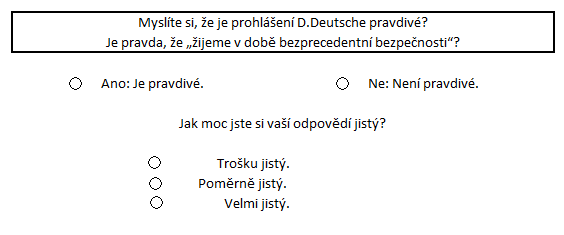
Sherlock Holmes by se divil, aneb co mají fonty společného s marketingem.
Položili jste si někdy otázku, jestli výběr fontů může ovlivnit rozhodnutí čtenáře?
Možná jste se nad tím nikdy nezamýšleli a píšete dál v Calibri. Možná vás ale zajímá, jak váš text podvědomě vnímají čtenáři a co všechno ten výběr tvaru písmenek může ovlivnit. Potom čtěte dál.
Baskervilský experiment provedl novinář E. Morris ve spolupráci s The New York Times v červnu roku 2015 a zúčastnilo se ho přes 45 000 respondentů. Wow, to je hodně lidí, že? Pokud to myslíte s marketingem vážně, i vás by mohly výsledky zajímat! Morris totiž přinesl odpověď na otázku:
„Může font sám o sobě zásadně ovlivnit to, jak vnímáme obsah sdělení?“
Lidský mozek vnímá velmi komplexně. A bylo by naivní myslet si, že když čte nějaké slovo, tak si představí pouze předmět, který ho reprezentuje. Nevnímá jen význam slova, vnímá zároveň tvary písmen, patek, mezery, hrany a křivky. Vnímá i umístění slova v textu. To vše mozek vyhodnotí, jako proces, který probíhá na pozadí našeho vědomí, zpracuje a přiřadí slovu emoci. Emoci, která se sváže s obsahem. Bezpečí, důvěra, kompetence, zábava…
Chiropraktici vědí jasně, které místo na těle zmáčknout, aby aktivovali určitý orgán. Já tvrdím, že stačí změnit tvar patek nebo šířku mezer mezi písmeny, a ovlivníte emoci vznikající v mozku čtenáře.
Zpět k Baskervillskému experimentu.
Skládal se ze tří fází. U prvních dvou se vám bude zdát, že nemají nic společného s marketingem, ale vydržte, ve třetí je překvapivé řešení.
1. FÁZE – vzbudit emoce, zainteresovat publikum.
Morris publikoval článek s přitažlivým titulem „Jste pesimista, nebo optimista?“, který měl za úkol vzbudit v lidech emoce.
Kdo by se nechtěl trošku pohrabat ve svém egu, jestli vidí sklenici poloprázdnou, nebo poloplnou? Lidé milují takové krátké cesty do hlubin vlastní duše. Název tedy přitáhne pozornost a článek má za úkol vzbudit v lidech emoci ohrožení, strachu, prostě základní půd sebezáchovy.Morris v něm popsal trajektorii obřího asteroidu, který v blízké době proletí okolo Země. Přidal vyjádření, ve kterém NASA ujišťuje veřejnost, že žádné reálné nebezpečí nehrozí. Článek uzavírá vyjádřením známého matematika Davida Deutsche:
„Kdyby se kdykoli v historii lidstva až do 21. století přiblížil k Zemi v kolizním kurzu asteroid o průměru 1 km, znamenalo by to smrt podstatné části populace planety. V tomto ohledu, stejně jako v mnoha jiných, žijeme v době bezprecedentní bezpečnosti: 21. století je vůbec první období, kdy víme, jak takovému nárazu, který může nastat přibližně jednou za 250 000 let, zabránit.“
2. FÁZE – zapojení čtenářů.
Na konci článku je online hlasování, ve kterém čtenáři, kteří jsou již zainteresováni díky vzbuzeným emocím, vyjádří svůj postoj k vyjádření matematika Deutsche. Věřím mu, nebo ne?
Někteří mají strach, berou článek vážně. Jiní jsou v klidu a spoléhají na „dobu bezprecedentní bezpečnosti“. A další hlasují jenom ze zvědavosti. Jde přece jenom o to, kolik z nás je optimistů a kolik pesimistů…
3. FÁZE – odhalení pravdy
Překvapení přichází.
E. Morris neměl v úmyslu testovat optimismus, či pesimismus, ale vliv jednotlivých fontů na posouzení důvěryhodnosti tvrzení.
Tvrzení = prohlášení matematika Deutsche a šlo o to, jestli lidé vnímají, jakým fontem je napsané a zohlední to ve svém rozhodování „tvrzení je pravdivé“, nebo „tvrzení není pravdivé“. Právníkovi, který přijde na jednání v šusťákách, také asi uvěříte hůře, než pokud se dostaví v obleku…
Ale jak to provedli?
Ve spolupráci s redakcí The New York Times byli respondenti náhodně rozděleni do šesti skupin. Každé z nich se zobrazil jiný online test (obrázek z fáze 2). Přesněji, text byl stejný, ale napsaný JINÝM FONTEM. Morris vybral tři patkové a tři bezpatkové fonty. Baskerville, Computer Modern, Georgiu, Helveticu, Comic Sans a Trebuchet. Podívejte se, jak vypadají:
4. FÁZE – výsledek
Výsledky byly neuvěřitelné.
Experiment jasně prokázal, že lidé reagují na „důvěryhodnost“ fontu a jeho výběr má velký vliv na to, jakému tvrzení věří více a jakému méně.
Jednoznačným vítězem se stal font Baskerville.
Morris poté zveřejnil v novinách závěr testu s vysvětlením:
„Všichni víme, že jsme ovlivňováni řadou faktorů – o mnohých z nich ani nevíme. Mohou být fonty jedním z nich? Může pouhý výběr fontu ovlivnit, zda budeme věřit jedné věci spíše než jiné? Mohou fonty fungovat jako neviditelné kouzlo? Nebo kletba?
Nechápejte mě špatně. Zásadní pravda ve větě „Zlato má atomové číslo 79“ není závislá na fontu, kterým je napsána. Tato věta platí bez ohledu na to, zda je zobrazena v Helvetice, Georgii nebo dokonce nešťastném Comic Sans. Ale bude pro nás jednodušší uvěřit, že zlato má atomové číslo 79, když si to přečteme v Georgii, kterou používá The New York Times online, spíše než v Helvetice?“
Baskerville nezvítězil náhodou, je to patkový font, starý 250 let. Působí jako anglický gentleman (na rozdíl od Comic sans, který je takový neseriózní adolescent). Má pevné základy, harmonické proporce a budí důvěru. Podobný font používají seriózní noviny nebo právníci pro své smlouvy. Prostě někdo, na jehož slovo se můžete spolehnout. A je vidět, že i lidé, kteří se nad fonty nikdy nezamýšleli, tento „vzkaz“ podvědomě vnímají a fontu Baskerville důvěřují.
Můj oblíbenec je už od vysoké Garamond. Seminárky jsem psala velikostí 13, aby byl čitelností srovnatelný s tehdy dominantním Times New Roman (no jo, je to přes 15 let). V životopise ho používám dodnes, jinak font přizpůsobuji publiku a typu sdělení zcela automaticky a intiutivně, ale dodnes mě nenapadlo zamýšlet se nad tím hlouběji. Takže díky za otevření nové oblasti.